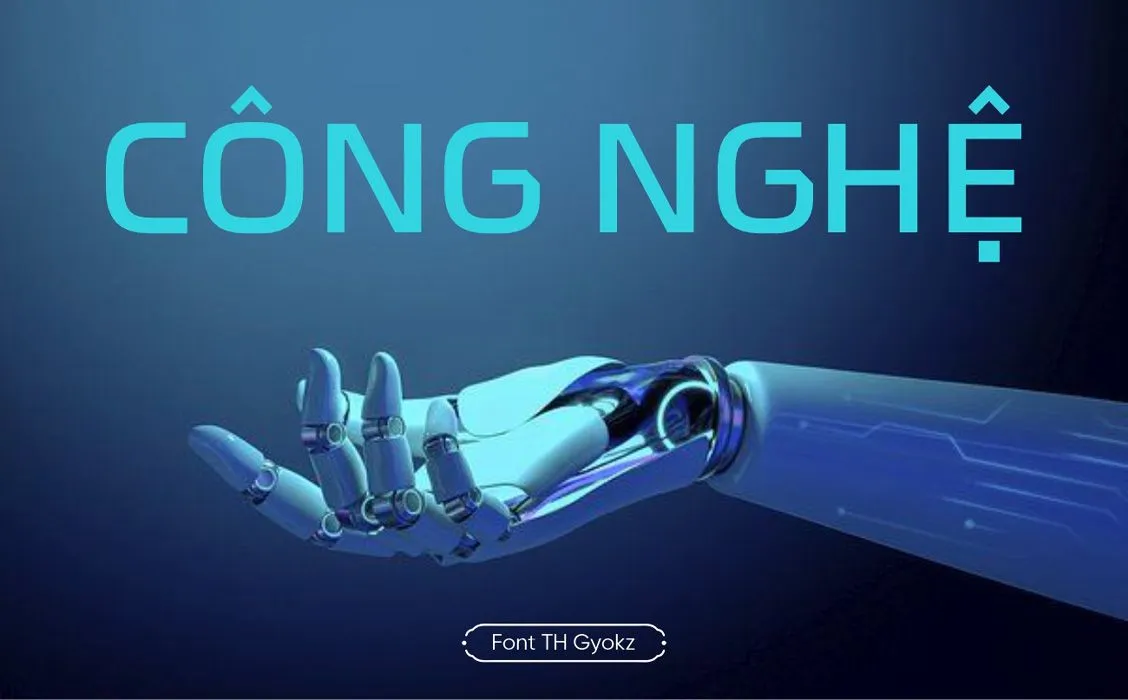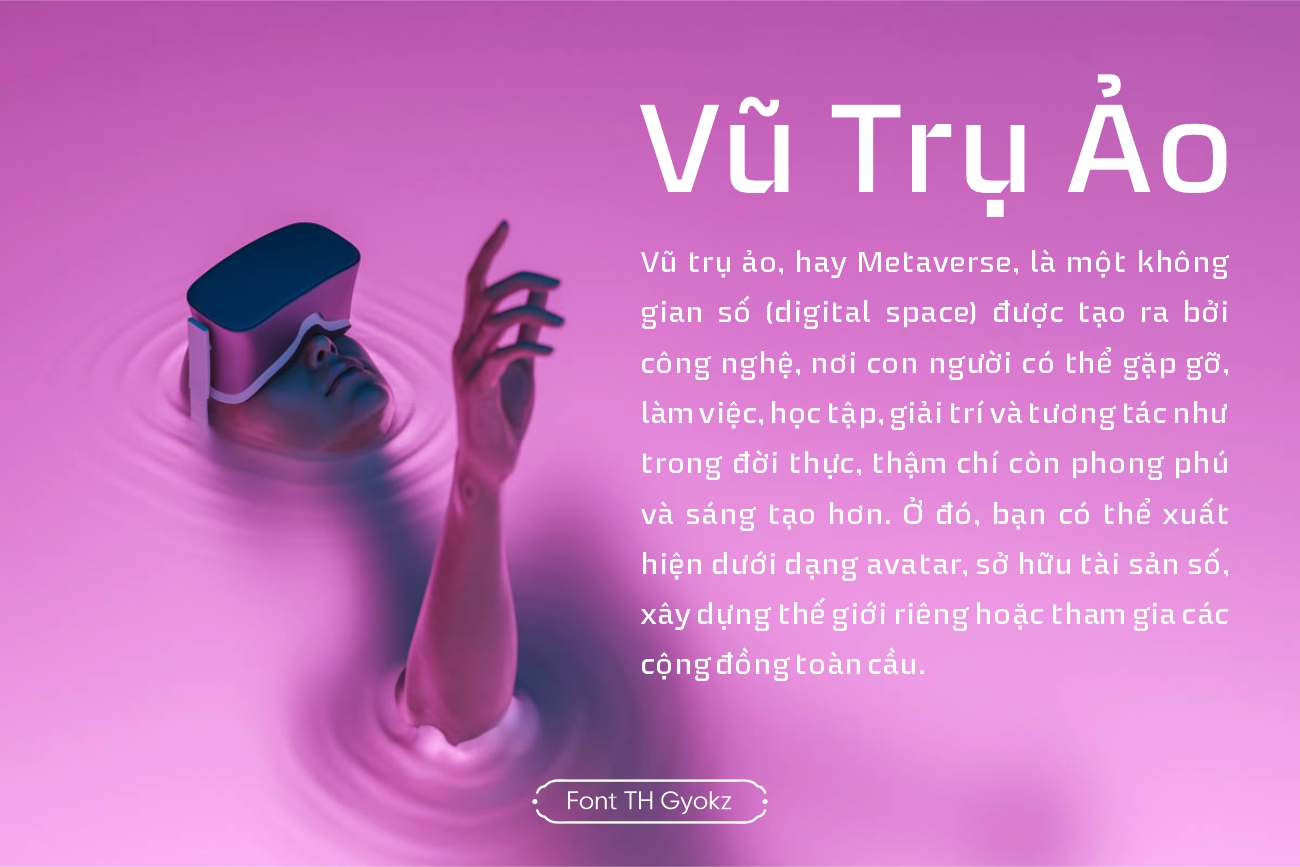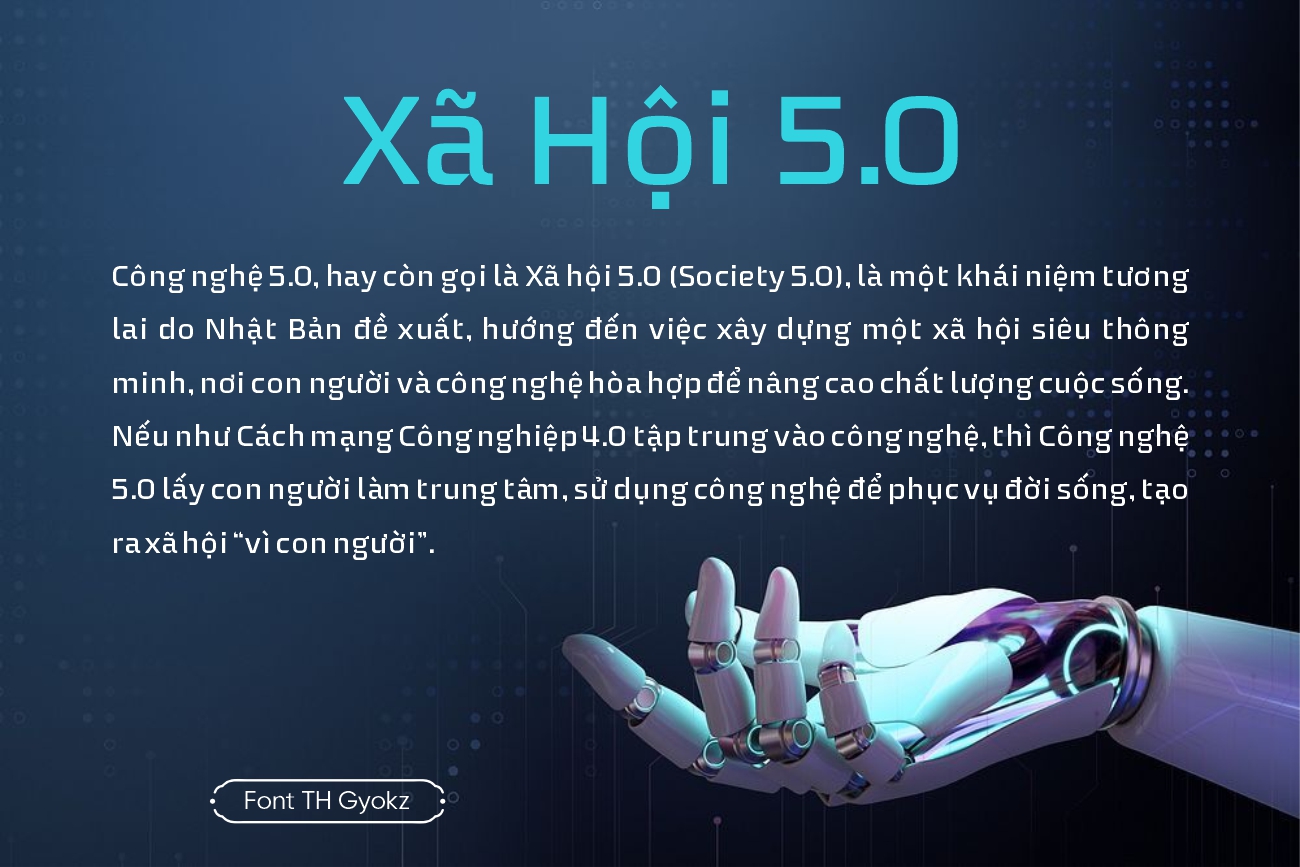
Trong dòng chảy không ngừng của thiết kế hiện đại, TH Gyokz (phiên bản Việt hóa từ Gyokz Sans) nổi lên như một biểu tượng của sự giao thoa giữa công nghệ và cảm xúc. Không còn những nét vẽ khô khan, bộ font này mang đến vẻ đẹp của sự "tự tin tĩnh lặng"—một chuẩn mực mới dành riêng cho các Designer Việt.
Ngôn ngữ thiết kế Futuristic: Sự kết hợp hoàn hảo giữa cấu trúc hình học gãy gọn và tỷ lệ nhân trắc học mềm mại. Đây là "vũ khí" lý tưởng cho các lĩnh vực AI, Blockchain, Fintech và Startup kỹ thuật số.
Tối ưu đa nền tảng: Hiển thị sắc nét từ giao diện UI/UX (Mobile, Web) đến các ấn phẩm Poster khổ lớn, đảm bảo tính hiện đại và chuyên nghiệp tuyệt đối.
Hệ sinh thái phong phú: Với 7 độ đậm nhạt (Weights) linh hoạt, bạn dễ dàng tạo ra sự phân cấp thị giác ấn tượng cho mọi dự án branding.
Việt hóa hoàn hảo bởi Team TH: Từng dấu câu được tinh chỉnh tỉ mỉ, đảm bảo dòng chảy văn bản mượt mà, không lỗi font, giữ trọn vẹn linh hồn của bản thiết kế gốc.
Nếu bạn đang tìm kiếm một mẫu font chữ công nghệ vừa đột phá, vừa tinh tế để nâng tầm dự án, TH Gyokz chính là câu trả lời xứng đáng nhất để trải nghiệm ngay hôm nay.